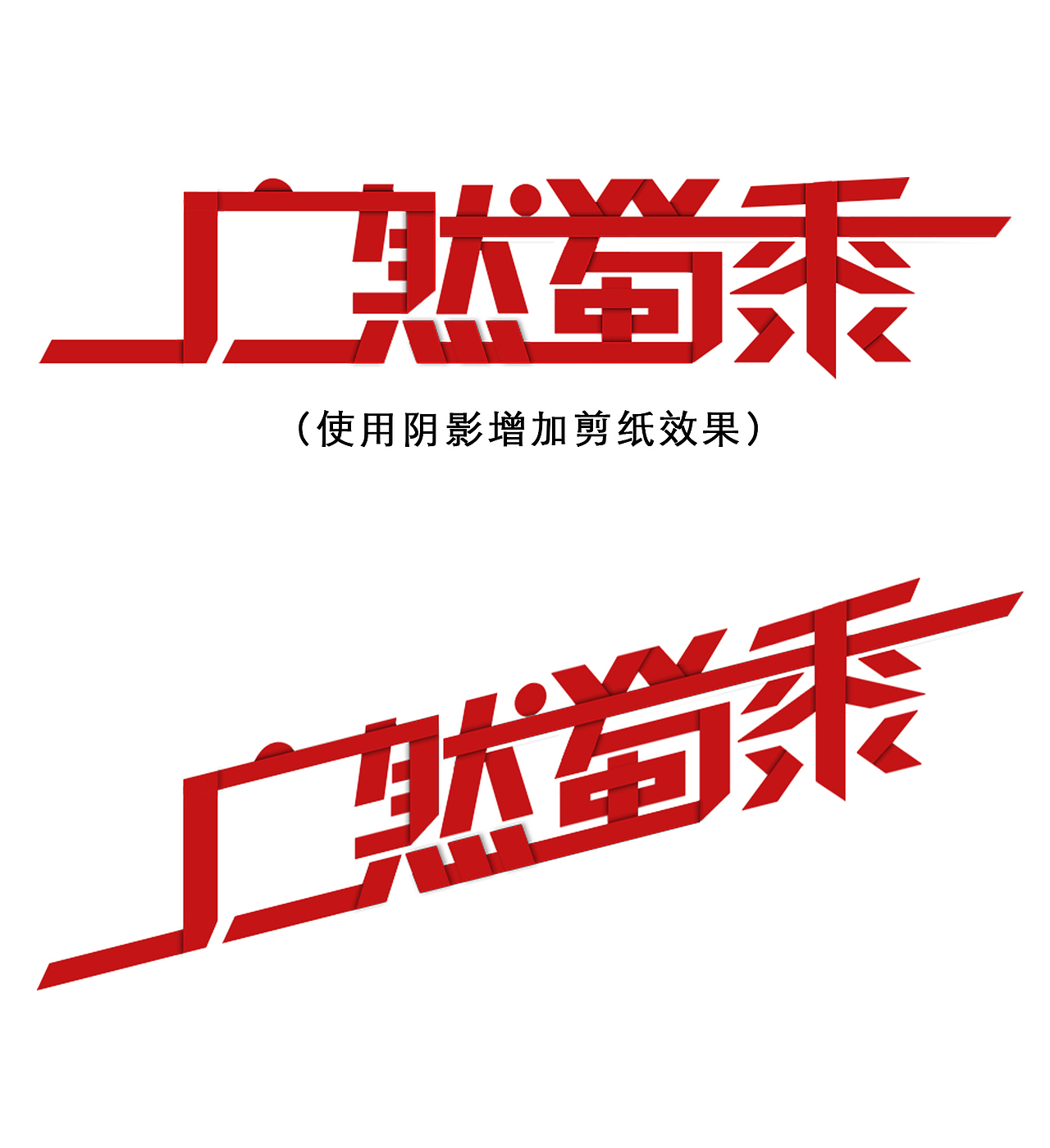
字体——剪纸效果
字体——剪纸效果(图ZMTkxMTcyMTI=) - 字体/字形 - 站酷设计师geraint7原创素材 - 站酷ZCOOL
字体——剪纸效果(图ZMTkxMTcyNzI=) - 字体/字形 - 站酷设计师geraint7原创素材 - 站酷ZCOOL
字体——剪纸效果(图ZMTkxMTcyNzY=) - 字体/字形 - 站酷设计师geraint7原创素材 - 站酷ZCOOL